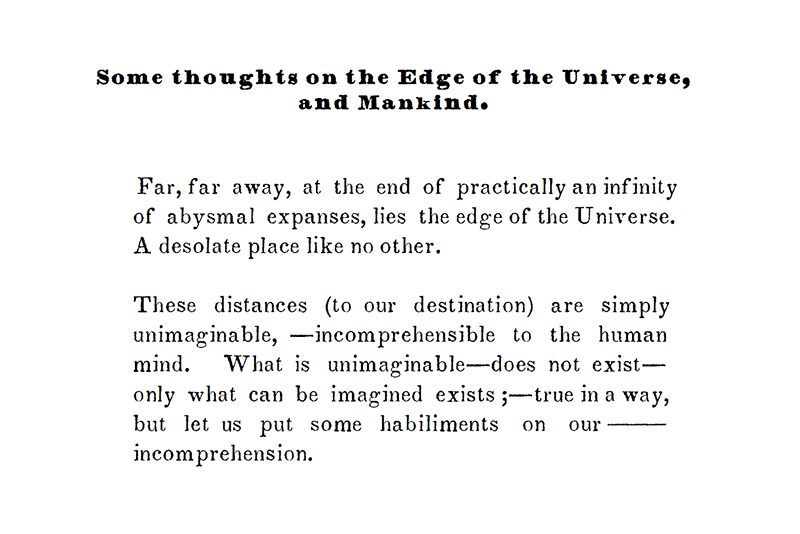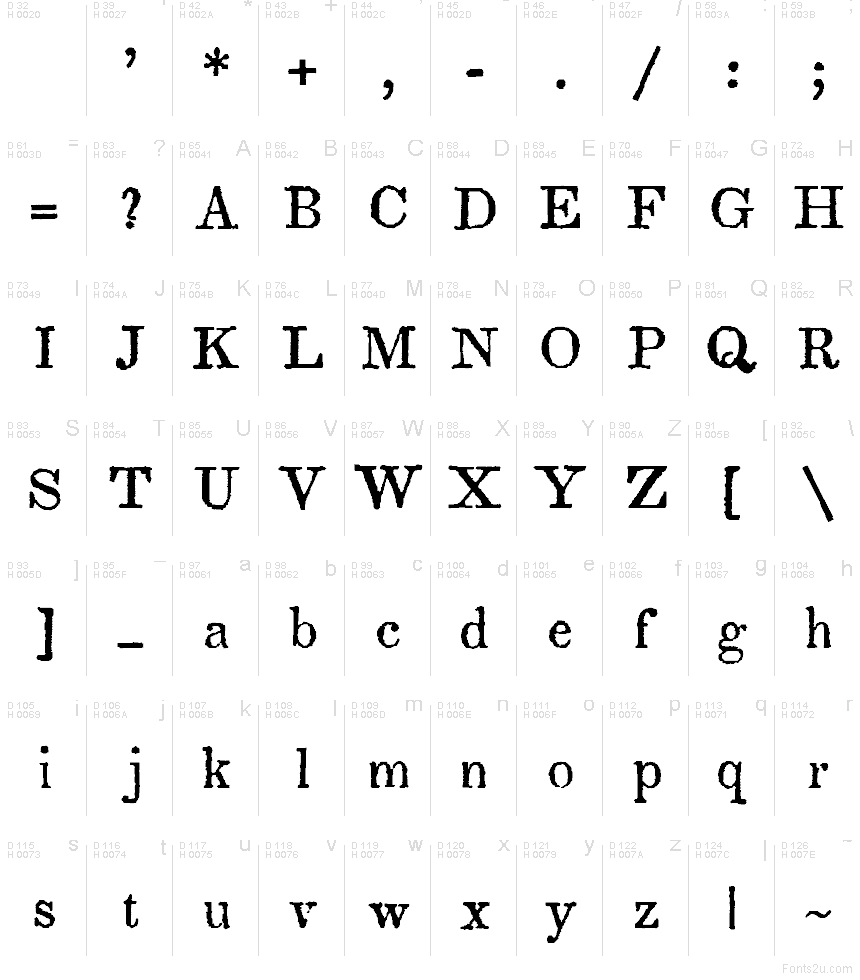
Southern Literary Messenger je bezplatné, lehce erodované písmo typu display, které má nádech opotřebovaného knihtisku a starých paperbackových titulů. Písmena mají drsné, nepravidelné hrany a skvrnitou texturu inkoustu, ale stále si zachovávají patkové tvary, které působí literárně a lehce formálně. Výsledkem je nálada, která má blíže k dobovým tiskovinám než k agresivnímu grunge stylu.
Hodí se na obálky knih, nadpisy plakátů, branding kaváren, záhlaví fanzinů nebo titulní karty, kde má bezplatné písmo navodit atmosféru stáří, prachu a papíru, aniž by působilo přehnaně teatrálně. Použijte ho všude tam, kde chcete, aby krátké řádky nebo hlavní slova působila autenticky a s historií, s právě takovým množstvím nedokonalostí, které naznačují příběh.
Písmo Southern Literary Messenger je rekonstrukcí zaniklého a zastaralého písma z 19. století, kterou připravil Gary Stephens.